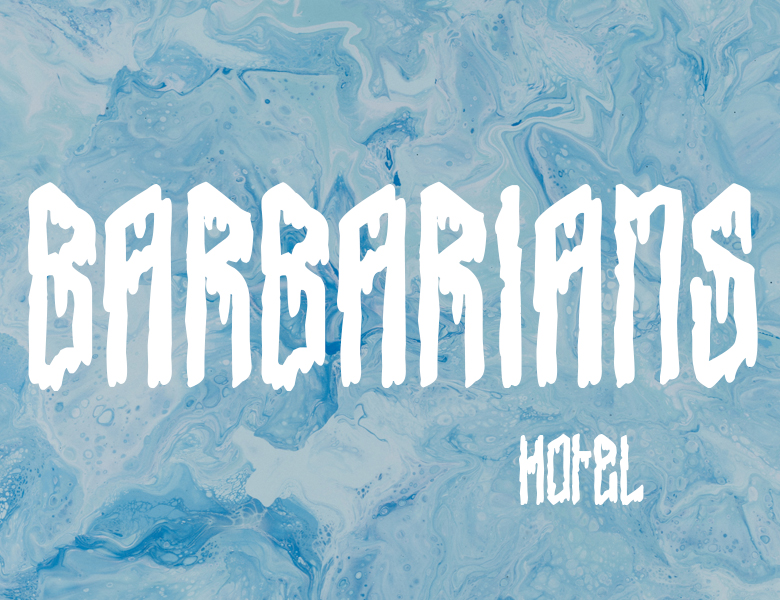
Barbarians Hotel字体
简介:Barbarians Hotel字体是一款很有个性的英文字体,粉刷笔触滴落的形状,让字体看起来更具有艺术感。视觉冲击力更强。该款字体风格:Regular;字符数:274;字形数:236;字体版本:Version 1.00;November 4。适用于广告设计艺术设计或装潢设计等方面的字体,由站长素材提供免费下载,站长字体下载大全提供精选中英文字体素材。